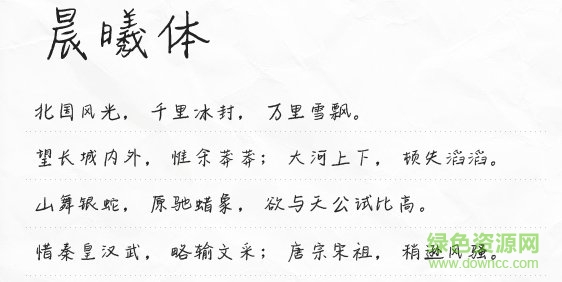
晨曦體ttf是一款硬筆書法字體,干凈利落的筆觸讓文字更加傳達(dá)出彩,類似楷體與隸書的模板,更顯得不拘一泥,字跡清晰結(jié)構(gòu)鮮明,來綠色資源網(wǎng)即可下載收藏!
晨曦體出自于文道字庫,是一個龐大的字體家族,有著云煙體、星辰體、文道硬幣行書體、荼蘼體、時光記憶體等硬筆手寫字體,字庫完整,能滿足大家常規(guī)使用。
硬筆書法是書法藝術(shù)百花園中一朵璀璨的奇葩。它的書寫工具包括鋼筆、中性筆、美工筆、鉛筆粉筆等,以墨水或者粉狀介質(zhì)為主要載體,來表現(xiàn)漢字和其他文字的書寫技巧。具有攜帶方便、書寫快捷、使用價值廣等特點(diǎn)。它與毛筆書法的視覺區(qū)別在于筆畫的粗壯或纖細(xì),有如去其肉筋存其骨質(zhì)。但其成像的原理和運(yùn)動技巧有很大的不同,是兩種不同的運(yùn)動模式。